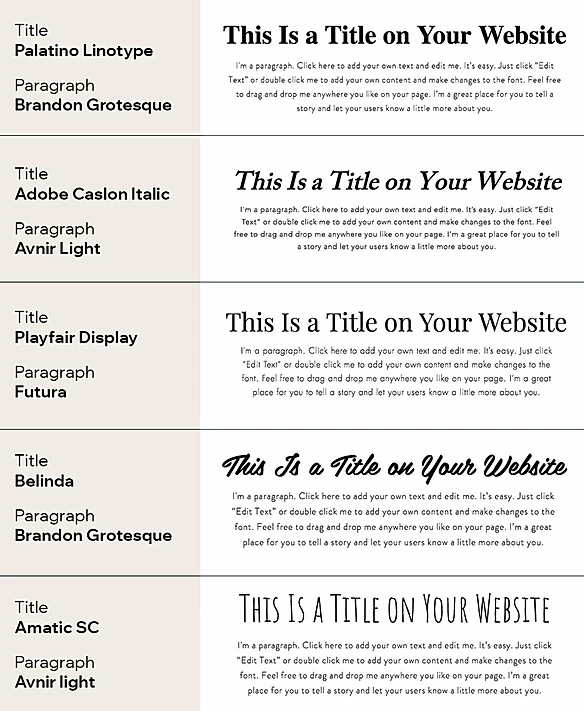
Я недавно заметил, насколько сильно влияют на мои ощущения при чтении такие, казалось бы, незначительные вещи, как шрифт и расстояние между буквами.
Правильный выбор шрифта, а также отсутствие боковых меню и всплывающих окон, значительно упрощают и улучшают процесс чтения.
Такие сайты, как Medium, Signal vs. Noise и Zen Habits, это все равно, что студии йоги в мире контента. То, как на этих сайтах представлена информация, умиротворяет меня во время чтения и позволяет полностью сконцентрироваться на истории, ни на что не отвлекаясь.
Вы только взгляните на разницу между Meduim и Cracked:
Экспонат А) Medium
Medium.comЭкспонат Б) Cracked
Cracked.comСравнив эти два сайта, сразу понимаешь, какой из них заставляет нас чувствовать себя паршиво.
На компоновку Cracked больно смотреть. Взгляд мечется из стороны в сторону, судорожно пытаясь определить, что и где читать дальше.
Поэкспериментировав с представлением материалов в блоге Crew, я понял, что нашу предрасположенность к определенным шрифтам и компоновкам можно объяснить с точки зрения науки.
Как мы читаем
При чтении наши глаза движутся определенным образом, следуя по так называемому пути сканирования.
Мы делим предложения на кусочки (саккады) и паузы (периоды фиксации). Вот путь сканирования типичного пользователя.
Путь сканирования обычного читателяВаш взгляд обычно движется по странице, останавливаясь через каждые 7–9 букв, чтобы осмыслить прочитанное. По мере того, как вы сканируете предложение, в мозгу не происходит никакой визуальной обработки. Визуальная обработка целиком и полностью зависит от информации, полученной во время паузы.
Итак, почему это имеет значение? При проектировании облика текста важно понимать, как мы читаем, ведь тогда вы сможете напрямую повлиять на связь читателя с вашим материалом посредством правильного шрифта или компоновки.
Почему правильный шрифт нам приятнее
Начав писать этот пост, я еще не был уверен, что найду научное объяснение тому, что мы относимся к определенным шрифтам определенным образом.
Я думал, что выбор шрифта — это, прежде всего, искусство с небольшой щепоткой науки.
Так мне казалось, пока я не не наткнулся на исследованиепсихолога Кевина Ларсона. Ларсон посвятил свою карьеру исследованиям шрифтов и недавно провел в Массачусетском технологическом институте (MIT) важное исследование о том, как шрифт и компоновка влияют на наши эмоции.
В ходе исследования двадцать добровольцев — десять мужчин и десять женщин — разделили на две группы. Каждой группе показали свою версию журнала The New Yorker; одной — версию, где компоновка, шрифт и расположение картинки были выполнены грамотно, а другой — версию с плохой компоновкой:
Исследователи выяснили, что читатели чувствовали себя плохо при прочтении отрывка с плохой компоновкой. Иногда они даже хмурились. Мышца, сморщивающая бровь (лат.
Тем временем, тем участникам эксперимента, которые читали статью с хорошей компоновкой, показалось, что они потратили на прочтение меньше времени, и они чувствовали себя лучше.
У этих людей отмечается более высокий когнитивный фокус, более эффективный мыслительный процесс и ярко-выраженное чувство ясности.
Исследователи сделали вывод, что хорошо спроектированная среда чтения не обязательно означает более высокий уровень понимания, но действительно вызывает у читателя приятные ощущения, вдохновляя и
Влияние культуры на предпочтения в шрифтах
Одним из объяснений нашего особого отношения к некоторым шрифтам является культура.
К примеру, шрифты Courier были созданы по образу и подобию старинных меморандумов, отпечатанных на машинке:
Связь шрифта Courier с печатной машинкойДля многих людей Helvetica связана с американским правительством, ведь именно этот шрифт используется для наголовых деклараций.
От этих ассоциаций сложно отделаться, и это нужно учитывать при выборе шрифта. Вот как выглядел бы сайт Банка Америки, если бы на нем использовался шрифт Impact, который ассоциируется с новостными заголовками:
Настоящий сайт Банка Америки:
Сайт Банка Америки со шрифтом Impact (который ассоциируется с новостными заголовками):
Сайт Банка Америки со шрифтом ImpactКогда шрифт меняется на Impact, Банк Америки перестает внушать доверие.
Поскольку шрифты создаются людьми, в ним обычно вкладывается определенный смысл. Никто не станет выбирать шрифт, который в его культуре ассоциируется с каким-то настроем, противоположным тому, что он хочет излучать.
Как сделать контент лучше
Качество контента — это, без сомнения, самое важное, но и то, как вы представляете этот контент (при помощи шрифтов и компоновки) заслуживает внимания.
Как говорил французский поэт Пол Клодель,
“Секрет шрифта в том, что он говорит.”
Так в какой же форме представить слова, чтобы вызывать у людей приятные чувства? Вот вам несколько методов, которые могут вам пригодиться, представленных экспертами в сфере типографики: